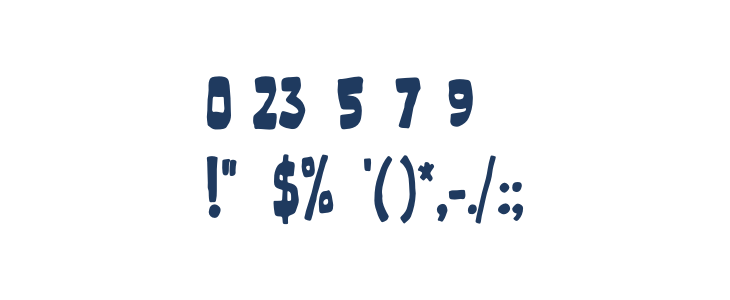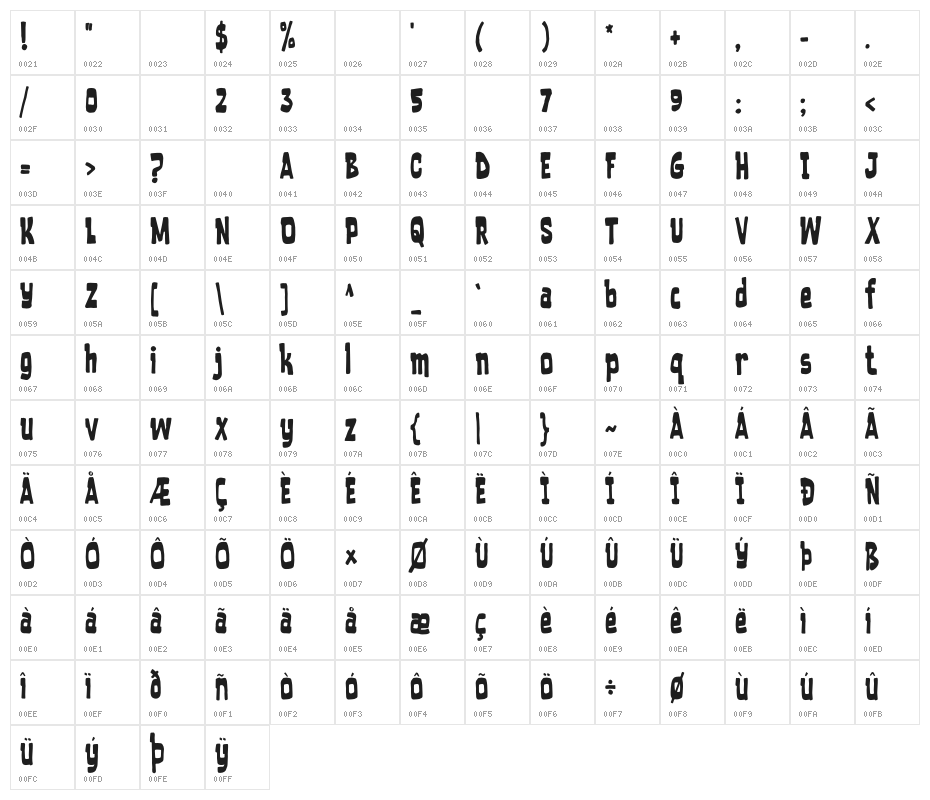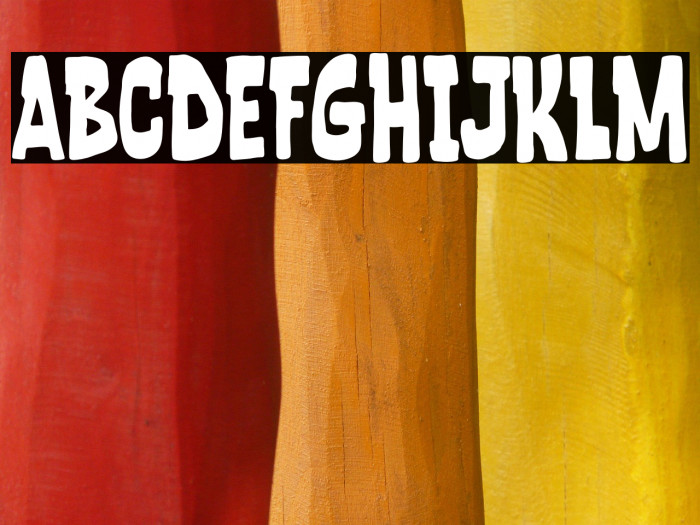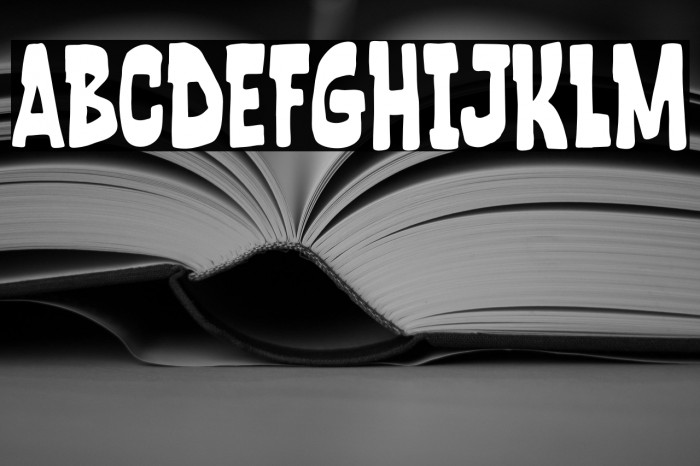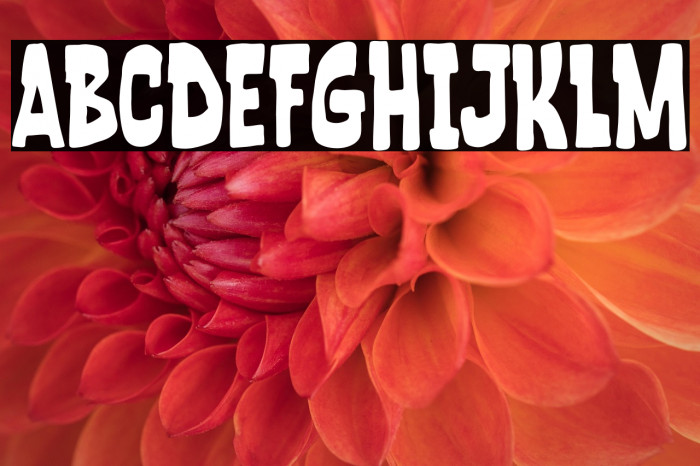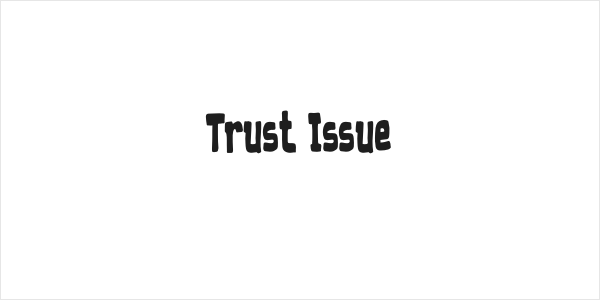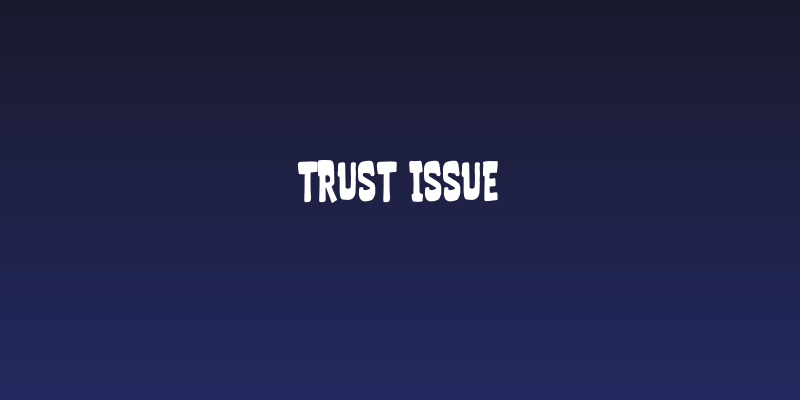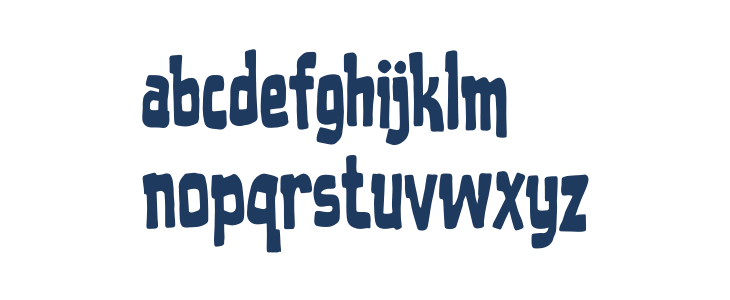
Trust Issue Font
| Stile generale | Playful, Quirky, Hand-drawn |
| Caso d'uso | Headlines, Posters, Creative Branding |
| Progetti proposti | Ideal for children's books, playful branding, posters, and creative invitations. |